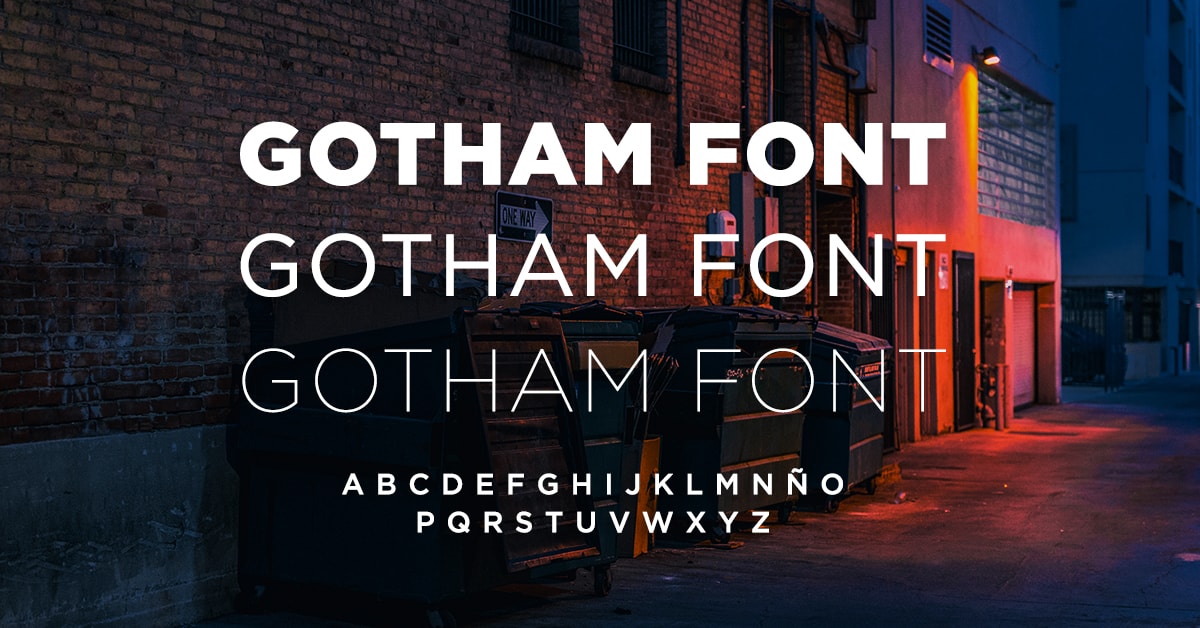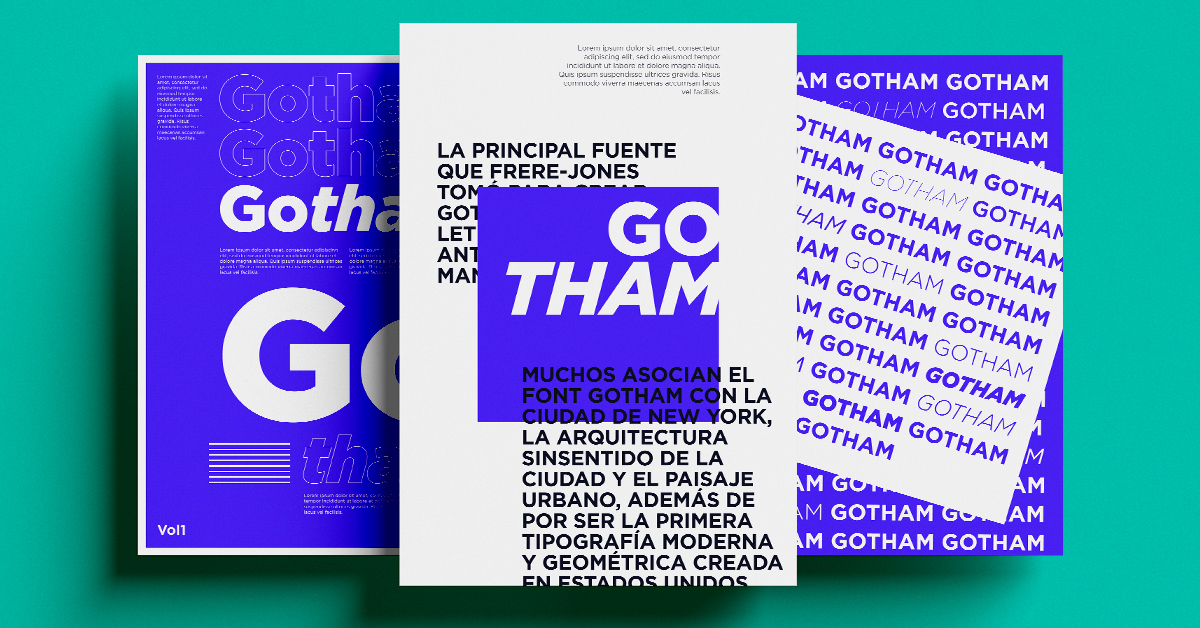
¿Has oído hablar de la tipografía Gotham Font? Si te interesa conocer todo de ella y destacar en el mundo de la publicidad y marketing, ¡has llegado al lugar perfecto!
Una tipografía es lo que usualmente se conoce como “estilo de letra” o “fuente de letra”. Entre las más conocidas están Arial, Times New Roman, Open Sans, Nunito y, la estrella de la noche, Gotham font.
La experta en diseño tipográfico, Rosa Rodriguez, explica en el curso online de Diseña con Tipografía: Técnicas y aplicación que suelen confundirse mucho los términos caligrafía y tipografía. La diferencia es que la caligrafía es un arte que se preocupa de la belleza escrita de las palabras y textos, mientras que la tipografía busca elaborar plantillas enteras con diferentes diseños y estilos.
Sabemos que existen infinidad de tipografías, cada una con un diseño y utilidad distinta. Por ejemplo, mientras que algunas tienen una apariencia más amigable, otras son utilizadas en contextos más formales.
Es probable que el nombre de “Gotham Font” te suene a la famosa ciudad en la que Batman vivía, pero el diseño de la tipografía es bastante sobria y sin muchos detalles extravagantes. Justamente, eso es lo que hace destacar a Gotham Font entre otras tipografías. No siempre los detalles excesivos son sinónimo de belleza. ¡Menos es más!
Si es que aún no conoces Gotham Font, ¡no hay problema! En el artículo de hoy, te enseñaremos cuáles son las características del tipo de letra Gotham, así como sus ventajas y desventajas. También, te dejaremos algunas referencias para inspirarte y, finalmente, te contaremos dónde puedes descargar Gotham Font y otras alternativas.
¡Anímate a conocer más de la maravillosa tipografía Gotham para complementar tus diseños!
La importancia de la tipografía en el diseño gráfico
¿Sabías que la tipografía puede transformar tu diseño por completo? A continuación, vamos a explicar la importancia de utilizar la tipografía ideal en una campaña de marketing y en el diseño gráfico.
Pensemos en la fiesta de Halloween. Seguramente, lo primero que se nos viene a la cabeza es la decoración terrorifica, peliculas de miedo, calabazas, los colores naranja y negro e, incluso, el tipo de letra que suele usarse en esa epoca del año.
Este día está asociado a lo tenebroso y oculto. Por eso, es casi imposible imaginar el nombre de esta fiesta con el uso de la tipografía especial de Coca Cola.
La importancia de la tipografía en el diseño gráfico es total porque el tipo de letra transmite significados y emociones. Utilizar, por ejemplo, la fuente Gotham en un cartel de Halloween como el que mencionamos, le otorgaría un carácter de seriedad que no encaja mucho con la festividad tradicional del miedo y el terror.
La tipografía en los diseños debe tener armonía y coherencia con la imagen mental que las personas tienen sobre un evento o fiesta, y sobre los valores de una empresa.
Es por esa razón que, al momento de trabajar en una campaña de marketing o diseñar elementos de publicidad, es necesario brindarle un tiempo importante a elaborar o buscar una fuente que vaya de acuerdo al concepto general. No será igual la tipografía para una publicidad de venta de juguetes que para tarjetas de presentación de un estudio de abogados.
Tomando en cuenta lo que te comentamos sobre la Gotham font, no solo debemos utilizar una tipografía coherente, sino que también debe ser legible. En ocasiones, menos es más. Mientras menos pomposa sea la tipografía, más sencilla será de leer por las personas.
Por lo general, una tipografía con muchos remates (colas, arreglos, extensiones en cada letra) no es de fácil lectura a primera impresión. ¿Si diseñas un panel publicitario externo elegirías una tipografía con remates? Obvio que no, porque los conductores tienen apenas segundos para ver y entender tu anuncio.
Existen una infinidad de tipografías sin remates que te pueden ayudar a diseñar vallas publicitarias, dentro de ellas está Gotham Font.
Características básicas del funcionamiento de una tipografía
Por lo general, las tipografías tienen estilos que cambian de acuerdo al grosor de la letra. Cada una cumple una función dentro de un diseño y ayuda al orden de ideas que deseas transmitir, también llamado jerarquía del mensaje.
- Bold. Suele ser el estilo que tiene un mayor contraste, por lo cual destaca en todo el texto. Se caracteriza por tener letras más anchas y grandes, por lo cual se usa para títulos y subtítulos importantes. En el caso de Gotham Font, el estilo bold es muy similar al médium, pero con la impresión de estar en “negrita”.
- Medium. Utilizado para el cuerpo del texto. Suele ser el estilo tipográfico que más se observa, pero que, a su vez, pasa más desapercibido. A diferencia del caso anterior, el estilo médium se caracteriza por tener líneas suaves y delgadas, ya que su objetivo es que el texto sea de fácil lectura. Respecto a Gotham Font, su estilo medium es muy similar al estilo Arial, aunque con más contraste. Es característico por ser un estilo bastante formal.
- Light. Recomendada para datos adicionales de menor importancia, como, por ejemplo, textos que van en pie de página. Suele ser muy similar al estilo médium, aunque siempre tiene un tamaño menor y, en ocasiones, suele tener un efecto de transparencia. Justamente, en el caso de Gotham Font, el estilo light suele tener poca opacidad, lo cual hace que sea poco llamativa.
El uso correcto de los estilos de las tipografías permite comunicar el mensaje de manera eficiente. Así que generalmente no encontrarás el estilo light en un título, porque su uso es para mensajes que pretenden pasar sutilmente.
Ahora ya conoces cómo funcionan las tipografías, incluyendo a la Gotham Font. Ahora toca conocer cuál es la historia de la Gotham font, esta tipografía que cada vez es más utilizada en el diseño gráfico.
Historia de Gotham font
Es momento de empezar a conocer qué es y cómo surgió Gotham Font. Esta tipografía fue originalmente diseñada para la revista GQ donde los editores buscaban un nuevo tipo de letra para su contenido. El objetivo era encontrar un estilo masculino y fresco.
El creador de Gotham Font la fuente Gotham fue Tobias Frere-Jones en el año 2000. Si no has oído hablar de él, ¡descuida! Es un conocido diseñador tipográfico neoyorquino, que cuenta con su propio estudio de tipografía y enseña en la universidad de Yale.
Pero, ¿cómo nació la inspiración para elaborar Gotham Font? Según manifiesta él propio autor, todo nació durante una época en la que se dedicaba a la fotografía urbana. Es allí en la que se sintió atraído por la tipografía de los viejos edificios y el metro de Nueva York. Es así como nació el estilo simple y neutral muy característico de Gotham Font.
Sin embargo, eso no fue todo. En la creación de Gotham font, Tobias tomó ideas de una tipografía diseñada en la década de 1920. Esta fue la tipografía Futura creada por Paul Renner. Esta fuente representó el estilo general de la época, donde se comenzó con el diseño de tipografías con formas geométricas.
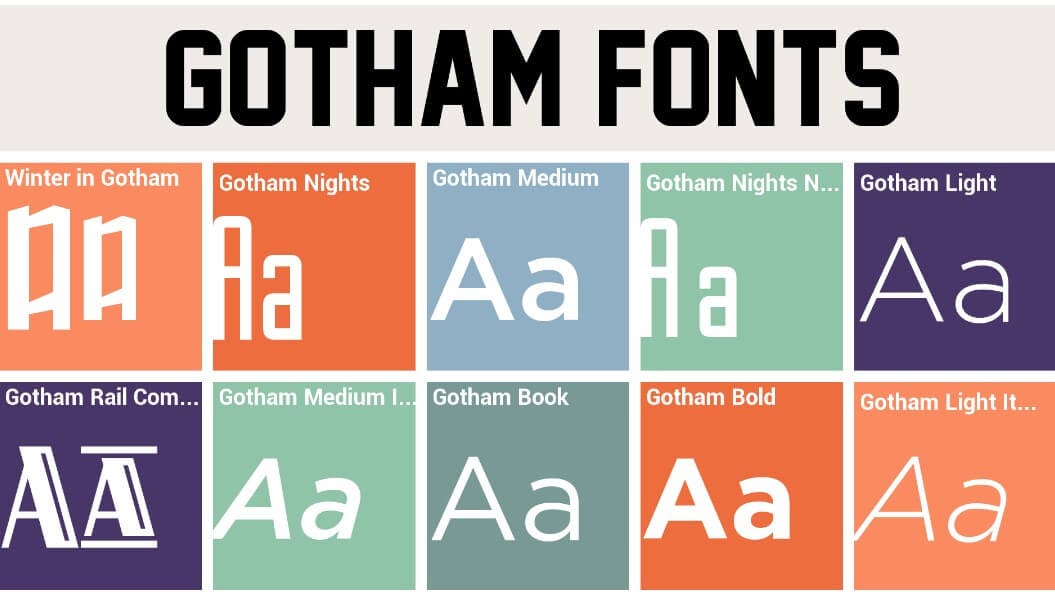
Por eso, la principal característica de Gotham font es que elimina los remates. Es la primera vez que mencionamos esa palabra, aunque es bastante conocida en el mundo del diseño tipográfico, ya que hace referencia a las extensiones que se ven en estilos como Lobster, Pacífico, Ultra, entre otras.
En el portal web Behance, se resumen los valores de Gotham font con 4 conceptos:
- Lineal
- Geométrico
- Vernacular
- Norteamericana
Según palabras del propio Tobias, el objetivo era crear una tipografía que no fuera del estilo de un diseñador, sino el tipo de letra que posiblemente crearía un ingeniero.
Muchos asocian a Gotham Font con la ciudad de New York y motivos existen. La arquitectura de la ciudad y el paisaje urbano son solo algunas de las cosas que están muy ligadas a esta tipografía. Gotham Font, además, es muy popular por ser la primera fuente moderna y geométrica creada en Estados Unidos. Sin duda, es una gran alternativa para tus trabajos y diseños.
Características de la tipografía Gotham
Ya conoces a grandes rasgos cómo nació Gotham Font, sin embargo, aún quedan ciertos aspectos por conocer que te van a permitir identificar a primera vista cuando se trata de esta tipografía tan clásica. Según la consultora web Behance, Gotham font tiene las siguientes características.
- Transmite identidad estadounidense. Como ya mencionamos anteriormente, es imposible desligar a Gotham Font de Nueva York y, sin duda, Nueva York es una de las ciudades estadounidenses más representativas. Aunque existen muchas tipografías que sean conocidas por llevar el sello del país norteamericano, Gotham Font tiene la ventaja de ser pionera en lo son las tipografías en Estados Unidos.
- Evoca diseños arquitectónicos, por el uso de líneas. No vamos a volver a repetir la historia de Gotham Font, pero si hay algo que destaca mucho en esta tipografía son sus finas líneas rectas en cada una de las letras. Definitivamente, una tipografía elegante y calmada.
- Estilo geométrico, evita remates en las letras. Si ves muchos detalles o curvas en las letras, sin duda no se trata de Gotham Font.
- Popularidad, usado por marcas como Fridays. No queremos profundizar mucho en este punto, ya que lo veremos más adelante. Sin embargo, es muy probable que no hayas notado que grandes marcas y campañas alrededor del mundo usan Gotham Font como su tipografía estelar.
- Flexible. Gotham Font consta de más de 60 estilos. Si bien una tipografía guarda ciertas características y elementos claves que no varían, existen varios estilos para diferentes utilidades.
Ventajas y desventajas de la fuente Gotham
Ventajas de la tipografía Gotham
Como hemos mencionado a lo largo de todo el artículo, Gotham Font es una tipografía que suele pasar desapercibida, pero que tiene muchas cosas por destacar. A continuación, te contaremos las principales ventajas de la fuente Gotham para que te atrevas a probarla en tus proyectos:
- Descarga y uso comercial libre. La gran popularidad y masificación de Gotham Font ha permitido que descargar esta tipografía sea una tarea fácil para cualquiera. Lo único que necesitas es buscar en tu navegador y encontrarás distintas alternativas, por supuesto, todas ellas gratuitas. ¡No hay excusa para no probarla!
- Tipografía de fácil lectura. Gotham Font destaca por su simpleza, permitiendo que los lectores no tengan problemas cuando se trabaja con ella. Si estás pensando en una tipografía para una revista o diario, Gotham Font es una buena alternativa para ti.
- Es un tipo de letra honesto, transmite verdad. Seguramente te preguntes: ¿Cómo una tipografía puede transmitir verdad? La verdad es que eso no es posible; sin embargo, el estilo elegante con el que cuenta Gotham Font transmite seriedad y madurez.
- Posee formas amables y poco, no rígidas.
- Transmite autoridad y respeto. Su carácter simple y su fama por ser usada en importantes revistas y periódicos le dan a Gotham Font cierto respeto ante el público.
Desventaja de la fuente Gotham
¡No es todo color de rosa! Así como cualquier aspecto de la vida, existen pros y contras. Es por eso que, a continuación, hablaremos de las desventajas de Gotham Font para que las consideres antes de darle uso.
La principal desventaja que encontramos es que, hoy en día, Gotham Font es tan conocida que suele ser usada en exceso, algunas veces incluso mal utilizada.
Sobre la popularidad del uso de la tipografía Gotham, Iván Villagómez de Innovation Workshop, señaló:
La cuestión a preguntarse sería, ¿acaso una tipografía puede ser desgastada y llegar a perder su valor? sí y no. Definitivamente una tipografía con el nivel de trabajo y dedicación como lo es Gotham jamás podrá perder sus propiedades estructurales y funcionales; sin embargo, no cabe duda que este uso indebido de la misma está comenzando a causar bastante ruido y notoriedad, al ser utilizada a diestra y siniestra, únicamente porque “x” marca de renombre se encuentra utilizándola.
La realidad es que Gotham Font no es una mala tipografía, incluso, nos atrevemos a decir que es una de las mejores. Sin embargo, las personas deben comprender que, al ser una buena tipografía, muchos la usarán. La idea es saber cuándo y cómo emplearla, ya que eso es lo que realmente potenciará tus diseños.
Por lo tantom date un tiempo para pensar bien en el objetivo de tu diseño y en el mensaje que quieres transmitir. Gotham font es genial si logras usarla correctamente.
Personajes y marcas que usaron Gotham font
En el 2002 la licencia de exclusividad de la fuente Gotham expiró. La tipografía fue liberada al público general y, desde ese momento, fue usada por periódicos y posters de películas. Es así como, rápidamente, se convirtió en una tipografía popular. Gotham font fue utilizada masivamente por su versatilidad.
¿Para qué sirve la tipografía Gotham? Pues para muchas cosas. Frecuentemente es usada en logotipos, pero es un buen complemento para tipografías de la familia Serif, aquellas fuentes que sí tienen remates o adornos en los extremos.
Barack Obama y Gotham
El uso más famoso de esta tipografía fue en la campaña presidencial de Barak Obama en 2008. Al parecer, el tipo de letra Gotham es la favorita del ex presidente. Además, en este caso específico, puedes apreciar que existe una coherencia con el diseño, ya que lo que se busca transmitir en una campaña presidencial es seriedad y simplicidad para comunicar un mensaje.
Spotify y Gotham
Otro caso importante del uso de Gotham Font es en el logotipo de Spotify. El auge de esta plataforma de streaming musical ha ido creciendo con el paso del tiempo; sin embargo, algo que pasa desapercibido en su logotipo es la tipografía. Como dato extra, la tipografía que se utiliza en la app también es Gotham Font. ¡Increíble!
Otras marcas que usan Gotham Font
Como último ejemplo de marcas famosas que usan la tipografía Gotham, tenemos al canal de televisión y estudio de animación Cartoon Network. Esta industria gigante ha cambiado de logotipo a lo largo de su historia, pero algo que siempre conservaron fue la tipografía Gotham.
La fuente Gotham se usó también en el logo de la Copa Mundial de la FIFA Brasil 2014, Saturday Night Live y Discovery.
¿Quieres usar la tipografía para tu marca? ¡Descarga este formato de Brandbook y diseña tu identidad corporativa!
Descargar Gotham font gratis
Lo mejor de todo, es que puedes descargar gratis Gotham Font desde su sitio web. Sin embargo, es necesario que conozcas sobre la familia de estilos de esta tipografía. En la página encontrarás las distintas variantes de Gotham font free.
También se incluyen otras tipografías muy útiles de las familias Serif, Sans Serif, Handwritten, entre otras.
La familia de Gotham font
Gracias a su popularidad, una variante redondeada (rounded) fue creada para la revista de diseño gráfico Print. En 2007 la exclusividad de Print terminó y esta variante se abrió al público.
En total, hay 66 estilos de la tipografía Gotham, incluyendo distintas variantes de acuerdo al grosor de la fuente. Narrow (delgada) y Extra Narrow (extra delgada).
Lista de algunos estilos de la tipografía Gotham:
Alternativas a Gotham font
A pesar que Gotham font tiene muchas variantes, puede que quieras cambiar el estilo para no usar lo mismo que el resto.
Por eso, si eres de los que quiere cambiar siempre, hemos preparado una lista de tipografías gratuitas que siempre serán de gran ayuda para tus diseños.
1. Montserrat
Diseñada por Julieta Ulanovsky, está inspirada en Gotham. Tienen un margen más amplio que le da un aire relajado.
2. Nexa
Las dos variantes de esta tipografía (Nexa Light y Nexa Bold) están disponibles para descarga gratuita. Es una fuente tipográfica muy expresiva con una diferencia notable entre mayúsculas y minúsculas. La forma básica de esta tipografía está inspirada en Gotham y se ve muy bien en proyectos de branding.
3. Raleway
Esta tipografía es geométrica, de la familia Sans Serif. Sus gruesos van desde Thin (delgada) hasta Black (negritas), todas acompañadas de su variante itálica. Tiene una clara inspiración en Gotham.
4. Visión
Esta alternativa a la tipografía Gotham ofrece un estilo de letra elegante y con buena legibilidad. Tiene muchos aspectos similares a Gotham Font, como, por ejemplo, el ancho de las letras y sus formas geométricas. Sin embargo, Visión tiene un aspecto más futurista y humanista. Al igual que las alternativas anteriores, esta es una tipografía gratuita.
5. Lato
Seguramente has oído hablar de esta fuente, ya que es una de las tipografías más famosas y usadas en Word. Fue elaborada por el diseñador Łukasz Dziedzic en 2010. Contiene más de 3.000 glifos en 18 estilos. Lato es una palabra en polaco, la cual significa “verano”, que busca destacarse como un estilo de letra serio, pero amigable a la vez.
Páginas para descargar más fuentes
A lo largo del artículo, te hemos contado todo lo necesario que debes conocer sobre Gotham Font, pero para gustos y colores no han escrito los autores. ¿A qué nos referimos? A que seguramente no a todos les guste esa tipografía.
Asegúrate de pasar un buen tiempo revisando las opciones disponibles en Internet, puede que encuentres justo lo que necesitas para hacer un trabajo excepcional.
Te vamos a recomendar una lista de páginas desde las cuales puedes descargar toda la familia tipográfica Gotham, tus fuentes favoritas, y sorprenderte con todas las opciones de fuentes creativas que hay para descargar.
Pero, antes de empezar, te recomendamos revisar nuestra selección sobre las más de 20 fuentes para títulos que son tendencia durante este 2021.
Estos son los mejores sitios para descargar fuentes gratis:
1. Google Fonts
2. DaFont
4. Urban Fonts
5. Font Space
En estas páginas encontrarás todas las variantes de la fuente Gotham y cualquier otra tipografía que necesites.
Tips para escoger una fuente
Si como comentamos al principio de la nota tienes un bloqueo creativo y te cuesta escoger las fuentes con las que vas a trabajar en tus diseños, tenemos algunos tips para que no utilices la Gotham font en todos y cada uno de los diseños que hagas.
- Lo primero que debes tener en cuenta, es el estilo de tu composición, de ello depende la tipografía. ¿Recuerdas nuestro ejemplo de la fiesta de Halloween? La fuente debe coincidir con el tema.
- Define para qué clase de formato necesitas la tipografía, porque puede que el tipo de letra Gotham quede perfecto para un título corto, pero no necesariamente tiene el mismo efecto en el cuerpo de un texto largo.
- Establece cuál es tu público objetivo, aunque no lo parezca, dependiendo de factores como la edad de las personas a las que va dirigido tu diseño, hay letras que pueden tener menos impacto que otras.
- ¡Utiliza las tipografías con sabiduría! No importa que existan miles de fuentes gratuitas para descargar, si combinas fuentes como Comic Sans y Gotham font, o mezclas muchas fuentes, puede que tu diseño no tenga una apariencia profesional. Debes mantener el sentido de la estética y estilo.
- Estudia las referencias y los diferentes usos que han tenido las fuentes que pienses descargar, así como con la tipografía Gotham, puede que algunas de las letras que deseas utilizar estén asociadas a trabajos muy famosos.
Estos son algunos breves consejos que te serán de mucha utilidad a la hora de diseñar y dejar que tu creatividad fluya. Te recomendamos visitar nuestro post sobre cómo combinar tipografías sin romper las reglas del diseño, así como este artículo sobre las mejores tipografías de números.
Imagen: Pexels
¡Hemos llegado al final de este artículo! Esperamos que conocer sobre Gotham Font te haya ayudado en tu tarea de elaborar grandes diseños.
No olvides que elegir la tipografía es fundamental para tu diseño. Por eso, siempre ten claro qué quieres transmitir a tu público objetivo o qué espera tu cliente en su diseño.
La creación de tipografías como Gotham font es solo una parte del diseño gráfico, lo más importante viene al momento de utilizarlas y lograr una composición armónica.